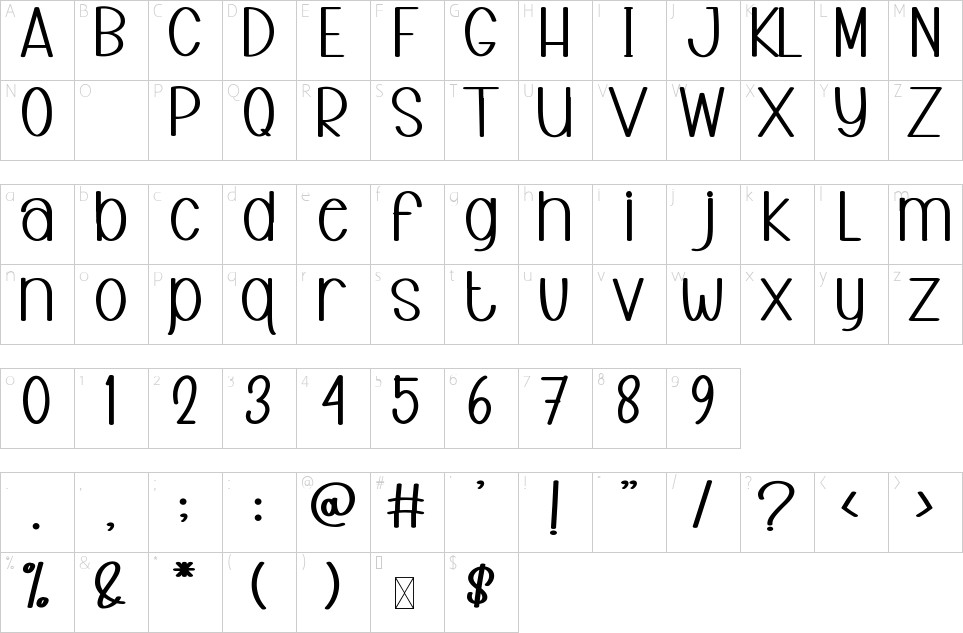
Aqui está uma descrição para a página de download da fonte ‘Disney Country Font’, seguindo as diretrizes fornecidas: Descubra a encantadora atmosfera do mundo dos desenhos animados Disney, diretamente no seu projeto de criação. A fonte Disney Country foi desenvolvida por InermediaSTUDIO e já teve mais de quatrocentas vezes que os usuários a baixaram para dar vida à sua arte, transformando palavras em uma forma única de expressão artística. Esse exclusivo conjunto de letras é perfeito para quem procura algo que transmita leveza e encanto ao criar mensagens digitais ou design gráfico. Composta com um toque de estilo Disney Country, essa fonte oferece aos artistas a oportunidade de fazer sua marca em qualquer projeto, seja ele uma simples mensagem digital ou elementos visuais mais elaborados. Não perca mais tempo buscando uma fonte que capture exatamente o espírito Disney e que se destaque no meio do seu trabalho. Baixe a fonte ‘Disney Country’ agora e inicie um novo capítulo de criatividade.